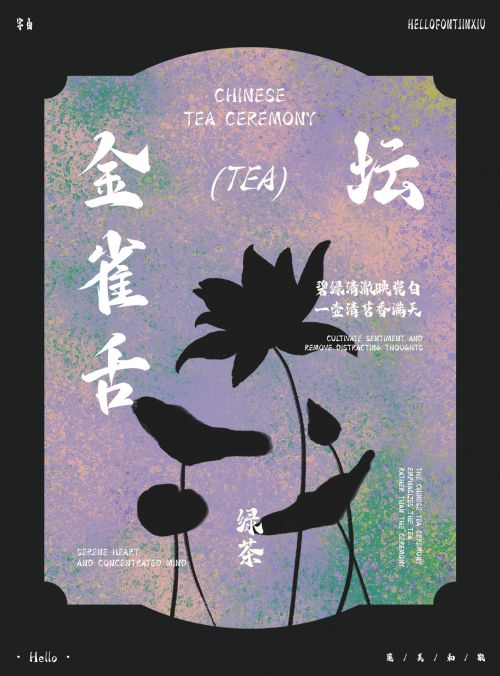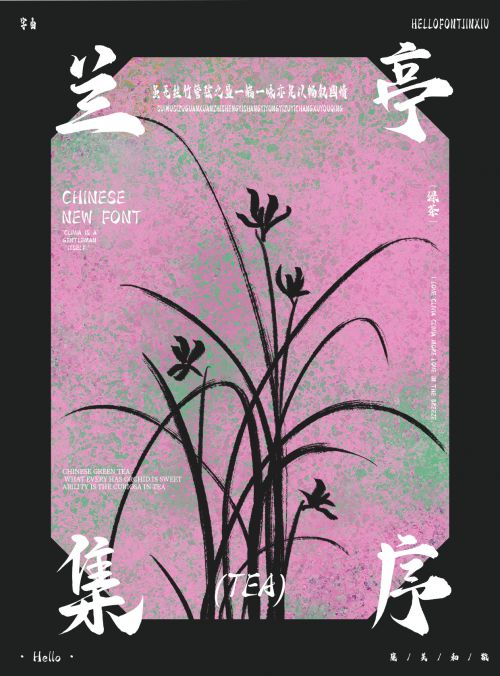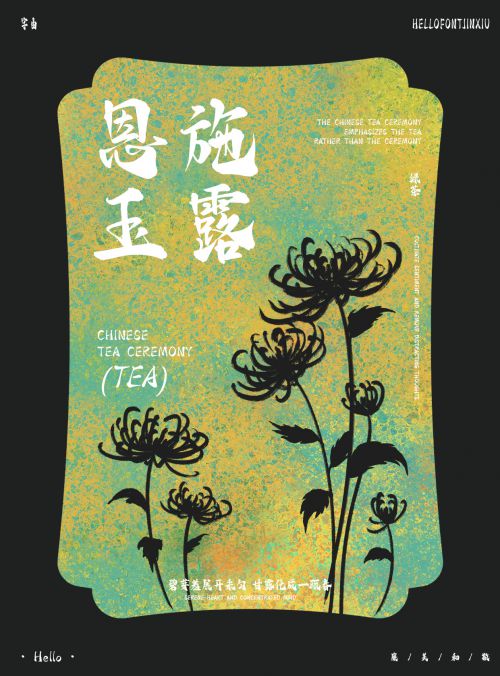
字由锦绣
字由锦绣是字由品牌推出的一款中国风手写体字体,以“繁花如锦,神采挥洒”为设计理念,融合古典韵味与豪放笔意,是兼具力量感与手写温度的商用优选。 字由锦绣字形方正稳健,重心居中且中宫宽博,既保证了整体结构的舒展大气,又通过留白营造出从容的视觉节奏。作为粗体手写体,其笔画设计尤为精妙:方头起笔利落干脆,传递出强劲力量感;末端的卷曲装饰则添古典雅致,似传统纹样中的流云卷草,尽显中国风底蕴。字体粗细均匀的线条避免了手写体常见的杂乱,断开的笔画连接让每个字既独立又连贯,既保留手写的灵动,又不失易辨识的实用性。 承袭“连带或迟或速兼而有之”的书写韵律,字由锦绣笔下“神采挥洒横逸”,既有“繁花如锦”的视觉丰富度,又不失“纵笔贯气”的流畅气韵,完美诠释了“洒脱大气”的风格内核。支持常规字符集,会员商用授权模式适配多元场景,无论是古典主题海报、文化宣传物料,还是需要传递力量感的标题设计,字由锦绣都能以其独特的“锦绣之姿”,让文字兼具美感与感染力。